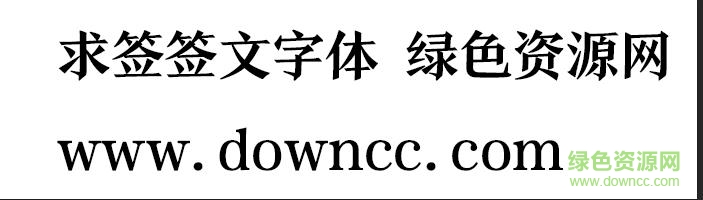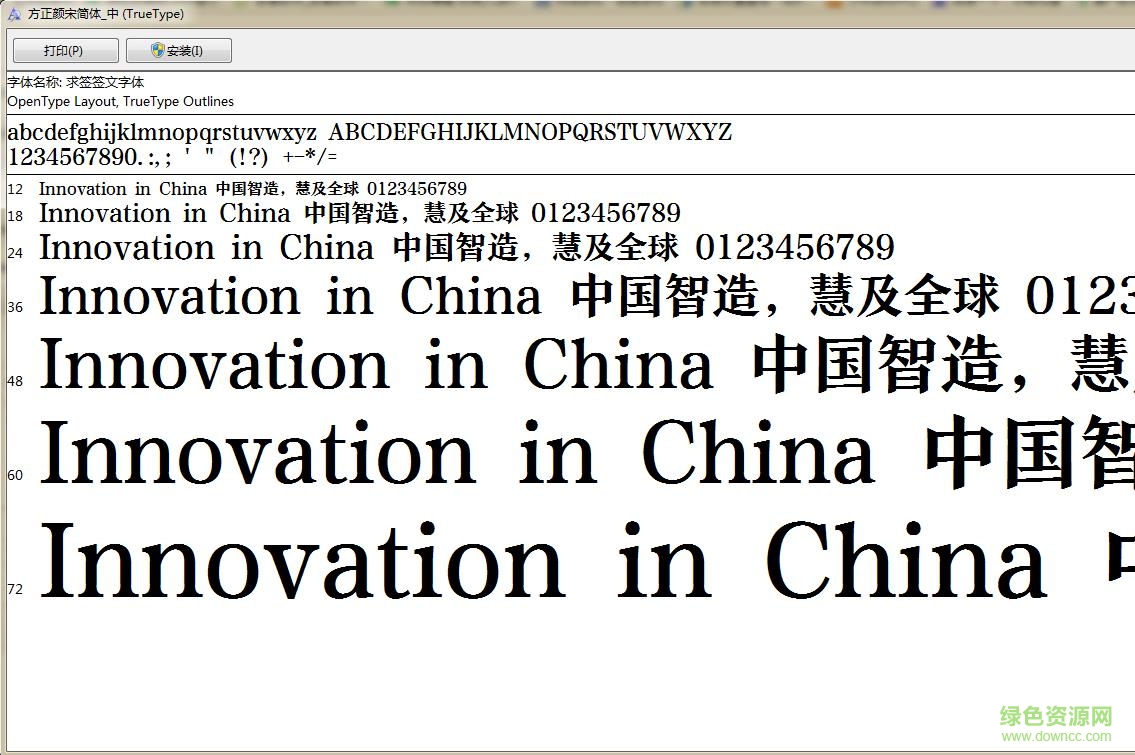
求簽簽文字體
簽文字體ttf是一款十分像簽文的字體,讓你在使用的時候能夠感受到最佳的體驗,是一款時下十分流行的網(wǎng)絡(luò)字體,運用范圍十分廣泛,廣受用戶們的喜愛哦!
求簽簽文字體小編點評
這款字體在媒體制作中十分不錯,它的樣式類似于黑體與宋體的集合,又獨具自己的風(fēng)格,讓你能夠獲得不錯的視覺觀賞效果!
簽文字體ttf字體介紹